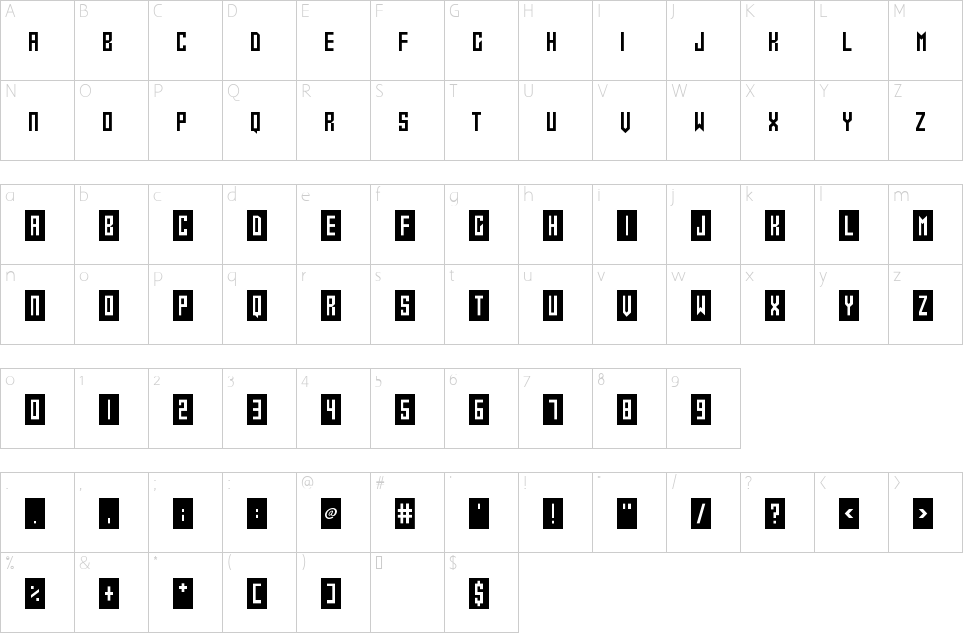
Gameshow Font – Download Grátis
Descubra a encantadora fonte Gameshow, ideal para adicionar um toque único às suas criações digitais. Especialmente projetada por Darrell Flood, essa elegante fonte está disponível gratuitamente tanto para Windows quanto para Mac. Com sua interface limpa e clara, Gameshow é perfeita para aplicativos de jogos, sites de entretenimento ou até mesmo logotipos de programas de televisão. O design moderno da fonte atraia olhares, tornando-a uma escolha ótima para criar um visual agradável e profissional em seus projetos digitais. Com apenas 15.516 downloads desde sua disponibilização gratuita, Gameshow já conquistou muitas pessoas que apreciam seu estilo acrobático e dinâmico. Seja você um criador de conteúdo, designer ou simplesmente alguém que valoriza uma boa fonte para seus projetos, Gameshow é a escolha perfeita. Baixe-a agora mesmo e deixe sua marca no mundo dos jogos digitais!